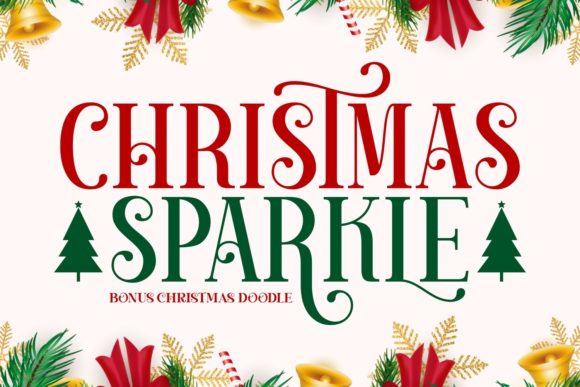
Creativefabrica Christmas Sparkle Font 2021
[Creativefabrica] Christmas Sparkle Font (2021)
Christmas Sparkle - это праздничный и стильный шрифт с засечками.